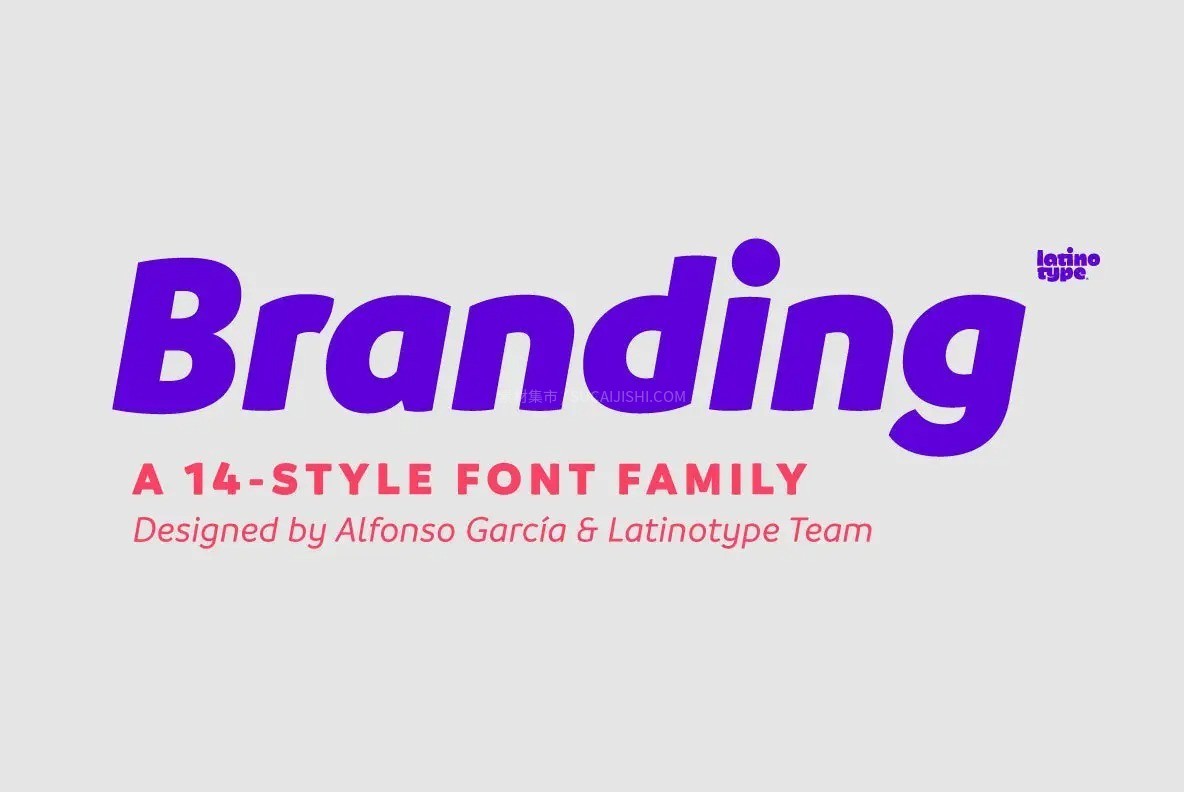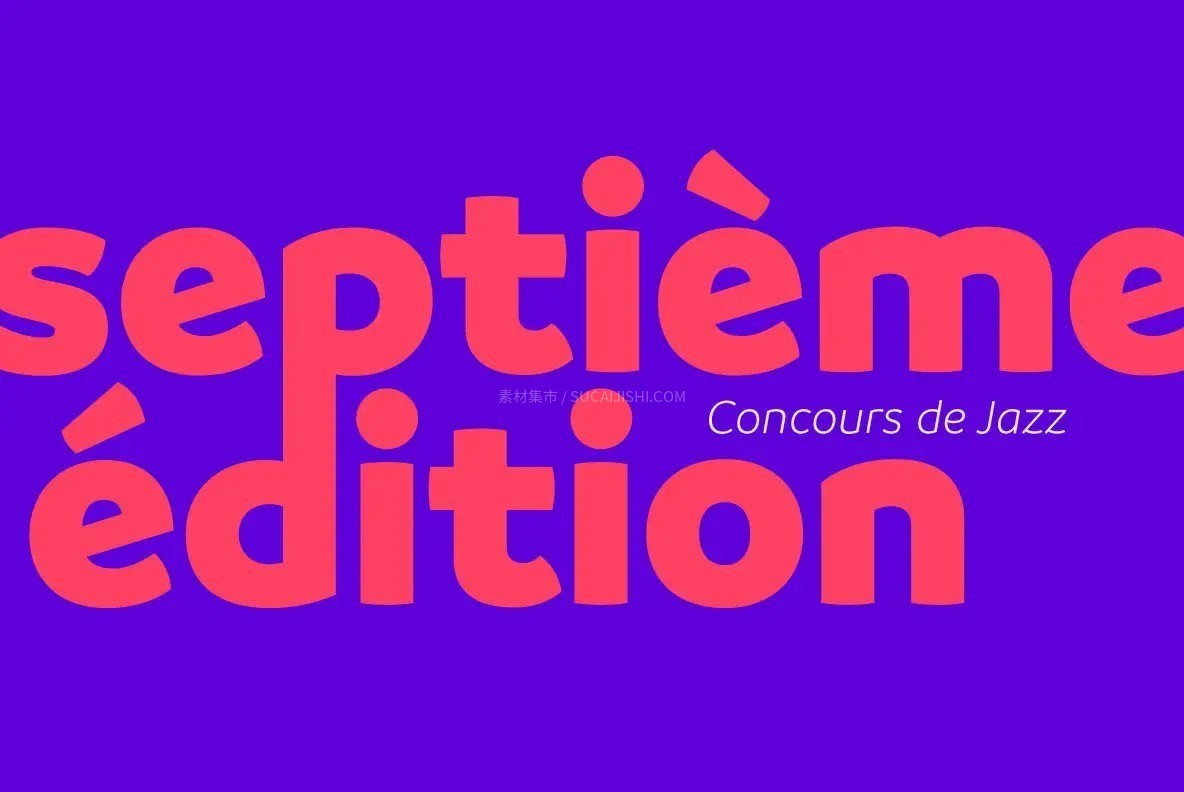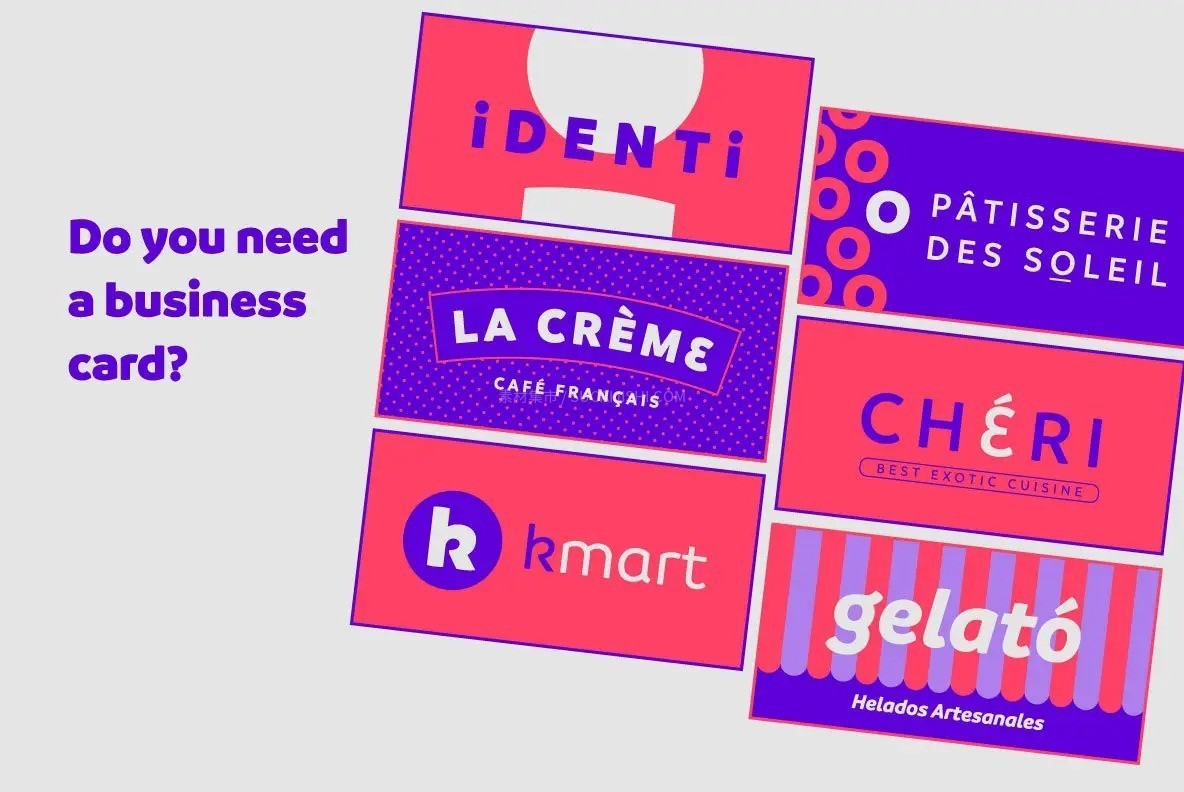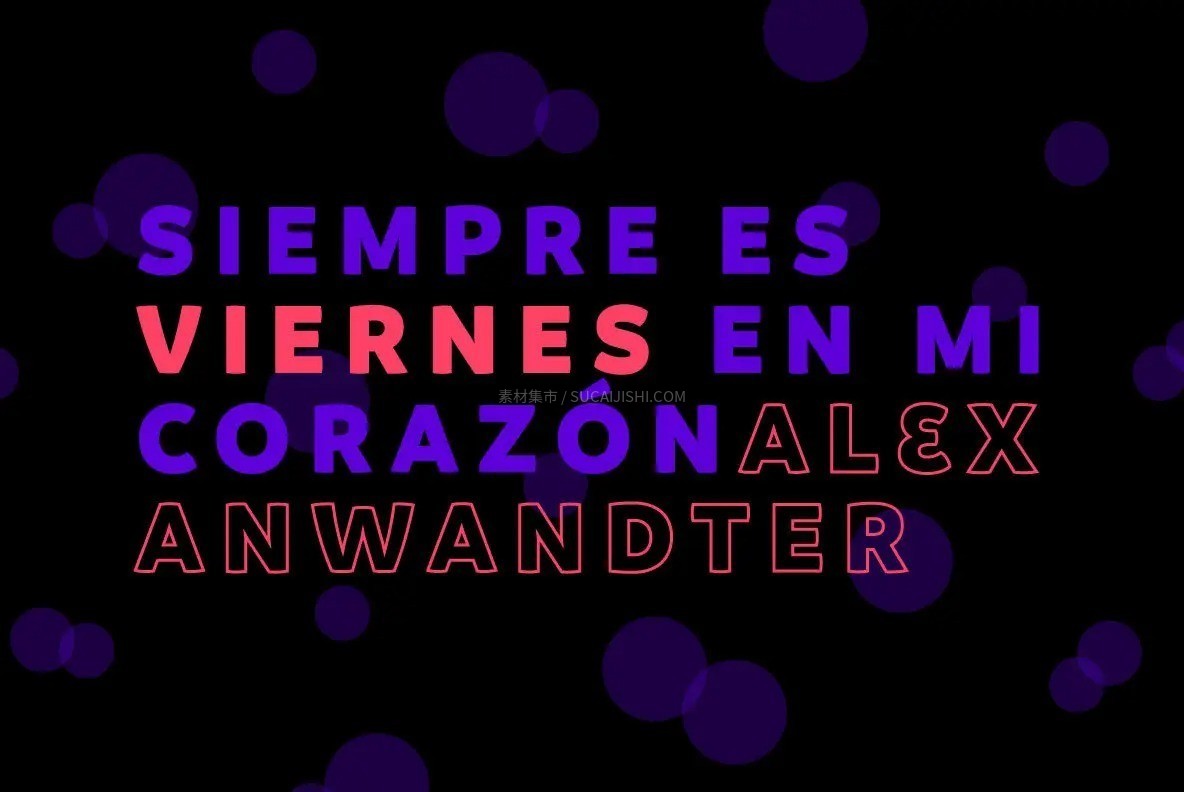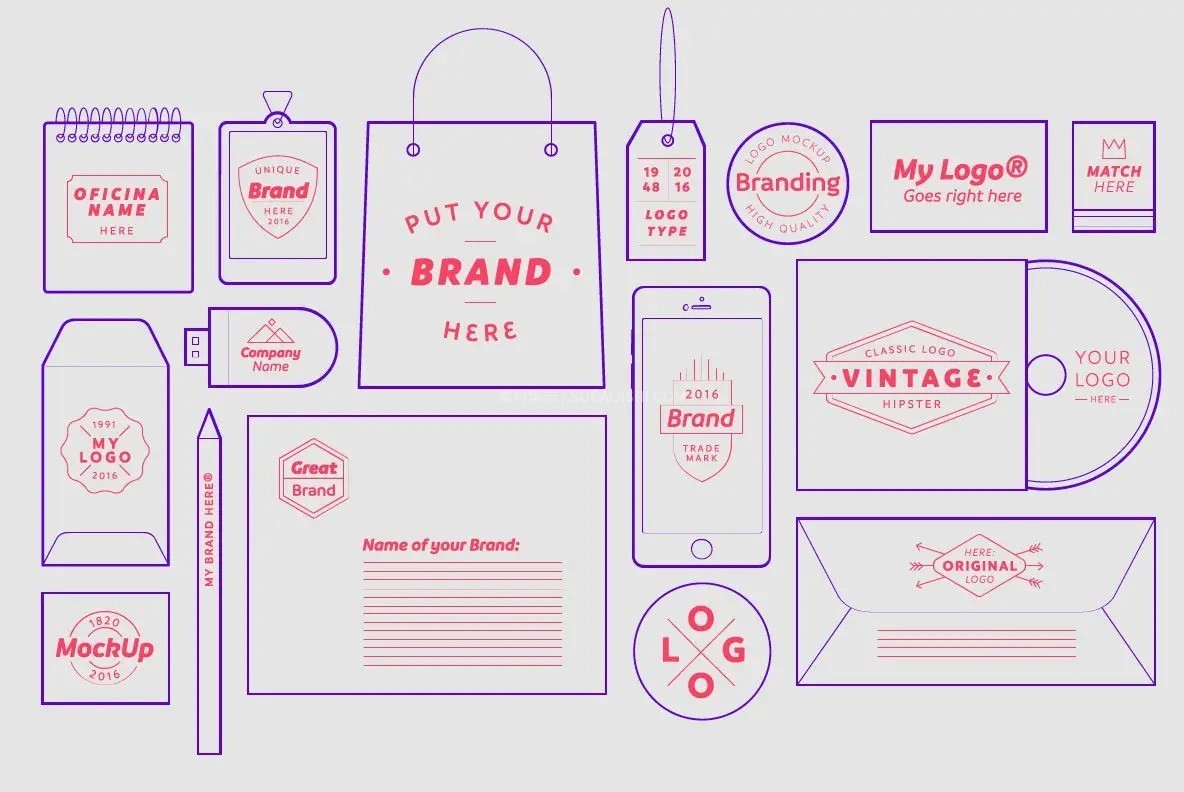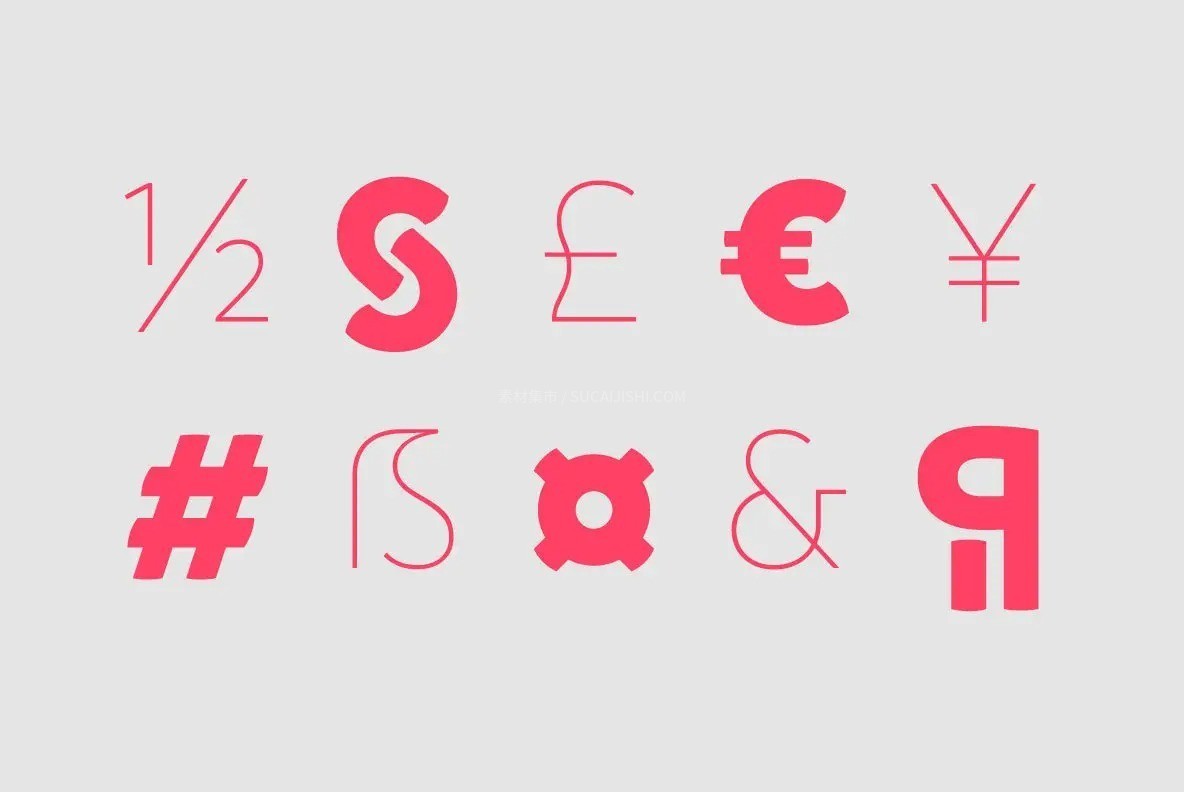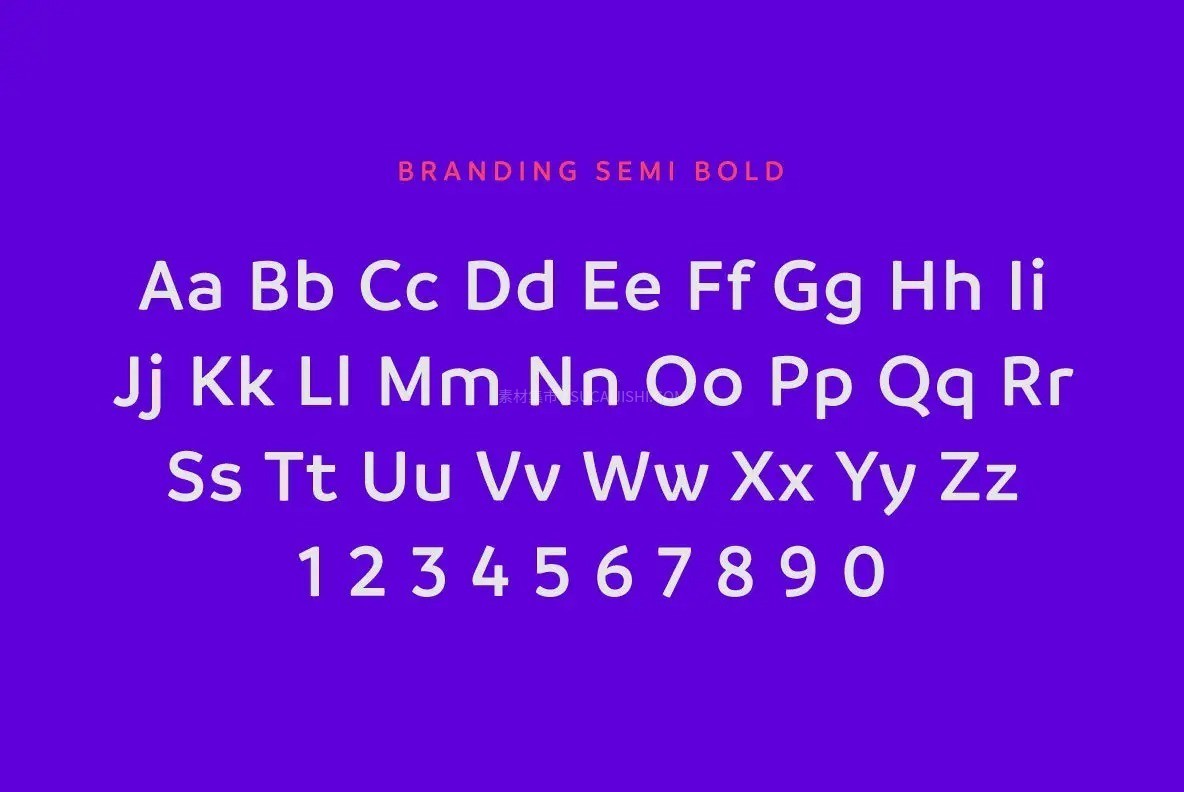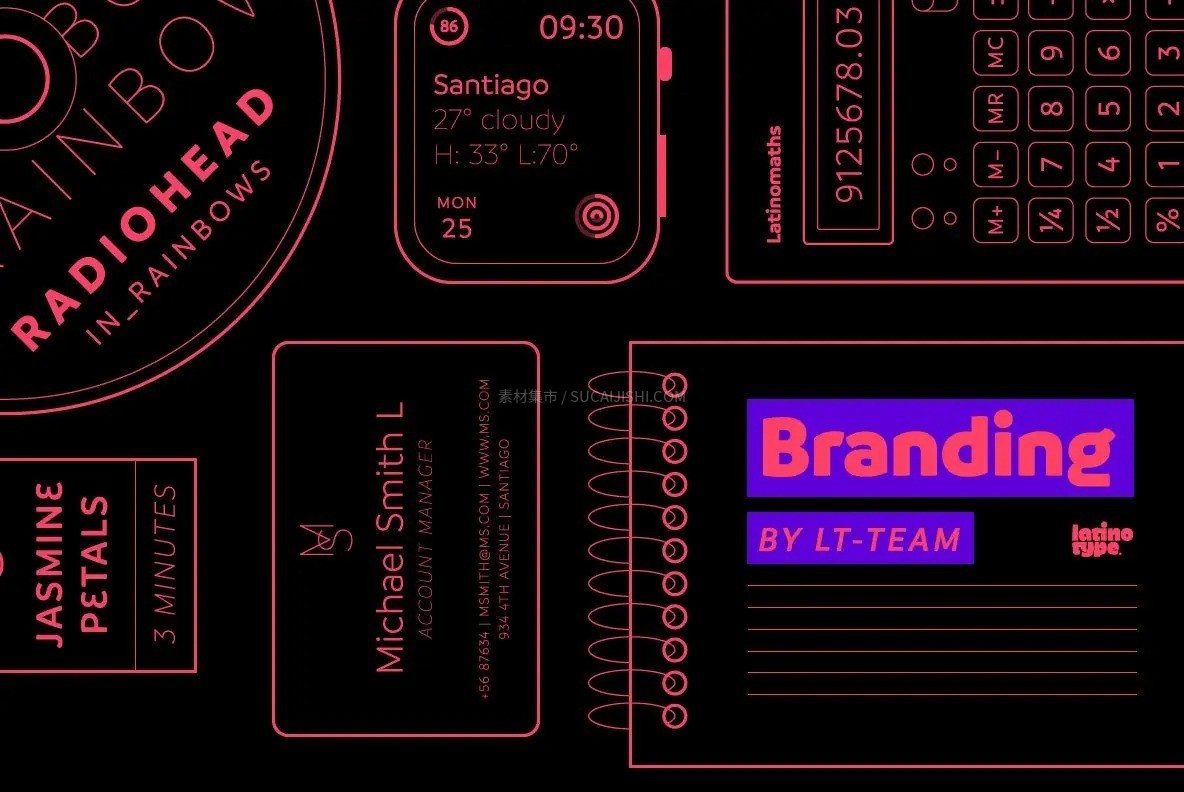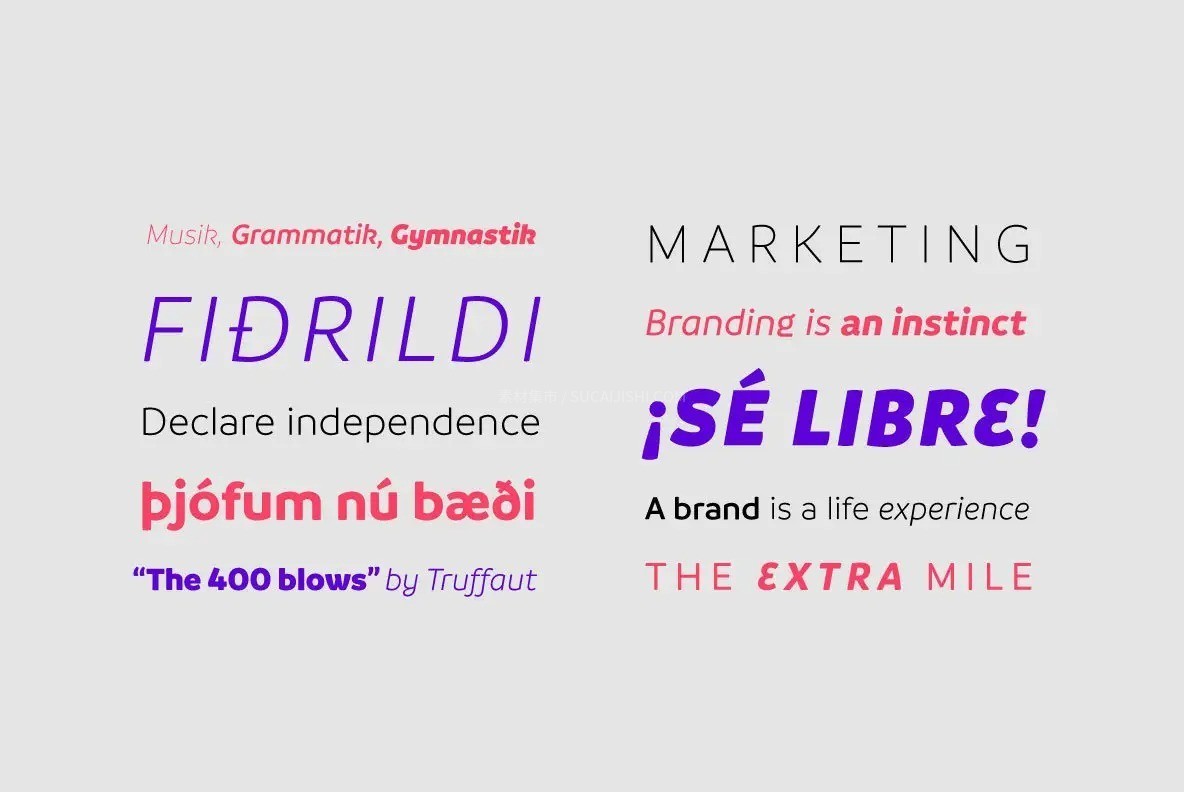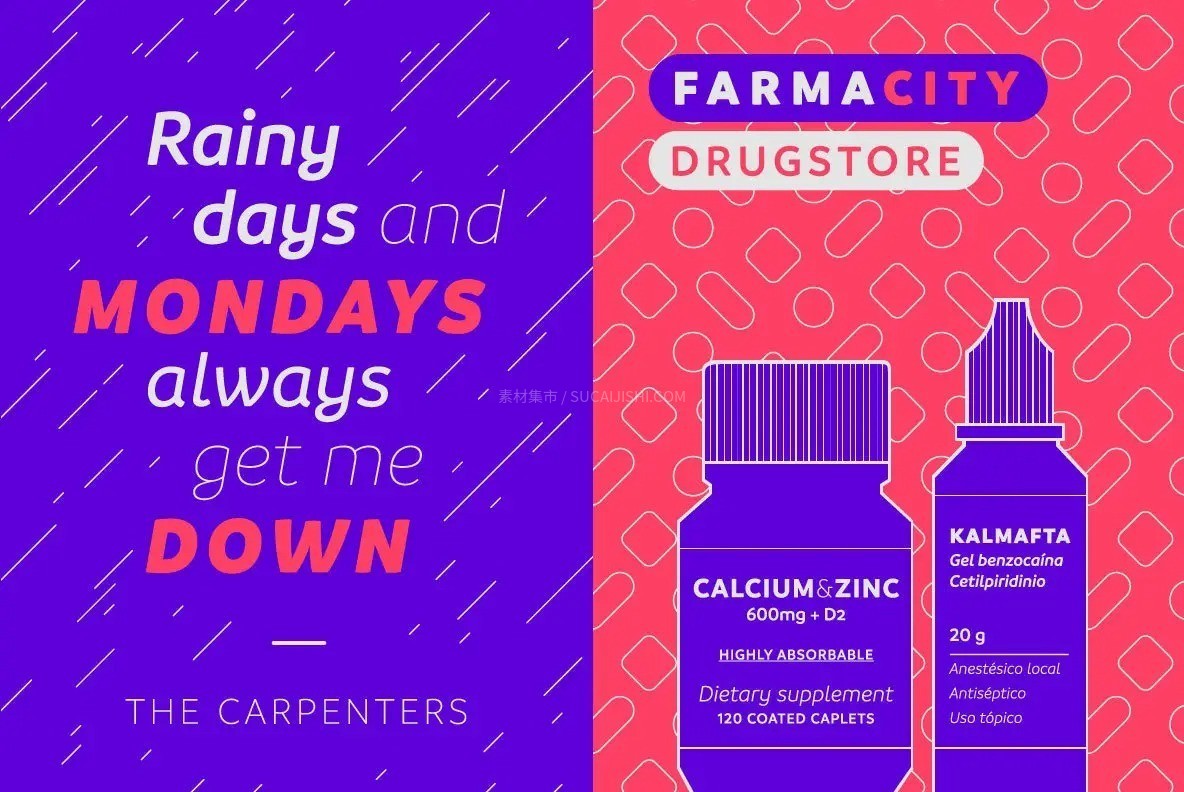
Branding现代无衬线家族字体
Branding 是一款专为当代审美与功能需求而生的无衬线字体。它巧妙地平衡了“严谨科技感”与“圆润亲和力”这两种对立美学,拥有中大 x 高度和略宽的水平比例。凭借平直的曲线笔画与独特的凸起末端,它能为视觉设计注入独特的现代质感。丰富的替代字符(Alt Characters)更为艺术总监和平面设计师提供了极高的创作自由度。
适用场景
品牌识别: 标志设计 (Logo)、同标字体 (Logotype)
视觉传达: 商业画册、海报标题、短文本排版、UI 界面设计
艺术创作: 概念设计、社交媒体封面、时尚杂志、电子产品包装
核心参数
字重规格: 提供从 Thin 到 Black 共 7 种字重,均配有相应斜体。
字符数量: 包含 544 个字符,支持 128 种语言(含欧洲重音符号)。
特色功能: 内含旧式数字 (Old-style Figures) 及多种样式替代字符。